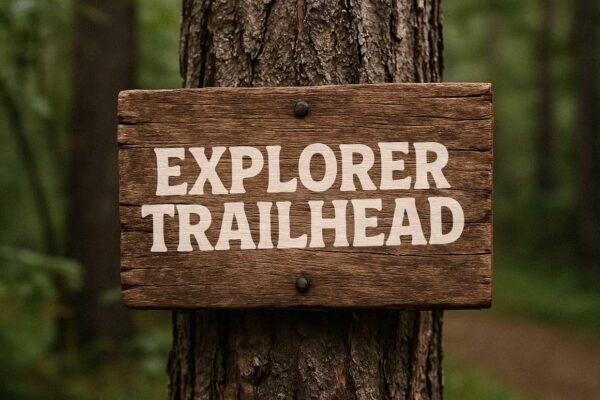
Wildkins Hiker’s – Sans Serif Font
Wildkins Hiker’s adalah font sans serif bertema outdoor dan petualangan, cocok untuk branding alam dan travel. Format OTF/TTF/WOFF, siap digunakan.
Wildkins Hiker’s adalah font sans serif dengan nuansa outdoor dan petualangan. Menampilkan bentuk huruf yang kokoh, bersih, dan mudah dibaca, font ini cocok untuk branding bertema alam, logo apparel hiking, kemasan produk outdoor, poster petualangan, hingga konten media sosial bertema travel. Wildkins Hiker’s menghadirkan kesan kuat, natural, dan fungsional dalam satu paket tipografi modern.
• Sans serif bergaya outdoor dan berkarakter kuat
• Ideal untuk desain bertema alam, hiking, dan adventure
• Termasuk huruf kapital, kecil, angka, dan simbol